“三极字库”,主要从事字形设计、字库产品开发、汉字信息技术研究,汉字应用技术研发等主营业务。“三极”之三代表了“一生二、二生三、三生万物”的中国传统文化理念。
新的一年,三极字库又给大家上线多款超豪华阵容的家族系列字体,让我们一起来看一下。
三极枫林简体的笔画设计为左细右粗,整体风格是向右边倾斜,字体风格飘逸随性,视觉效果抢眼,个性突出。该字体是一款家族字体,有4个不同的字重供您选择。
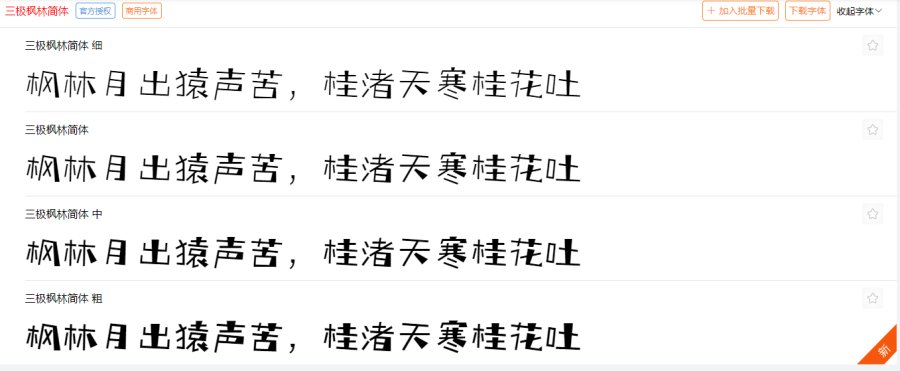
三极汉林简体其笔画横竖比例约为1:4,兼具了黑体的简洁和宋体的精致。字形方正,笔形简练,风格简洁优雅。这是一款拥有3种不同字重的系列字体。
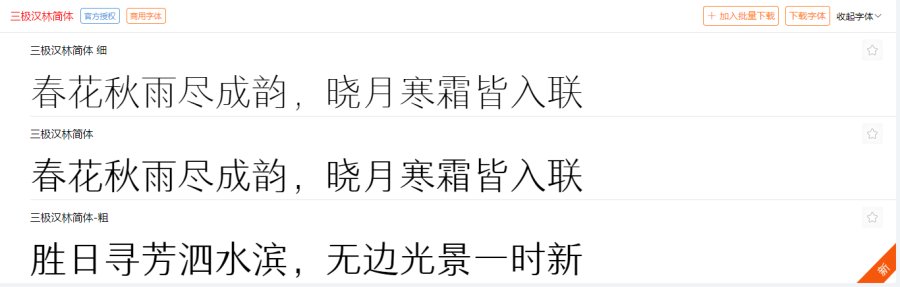
三极玩趣简体是一款带有手写风格的活泼漂亮的卡通字体,字体笔画简洁、错落有致,字体整体动感十足。与黑体相比字形更加随性活泼,不受拘束。该字体拥有5款字重,适用于广告、包装、海报等场景中。